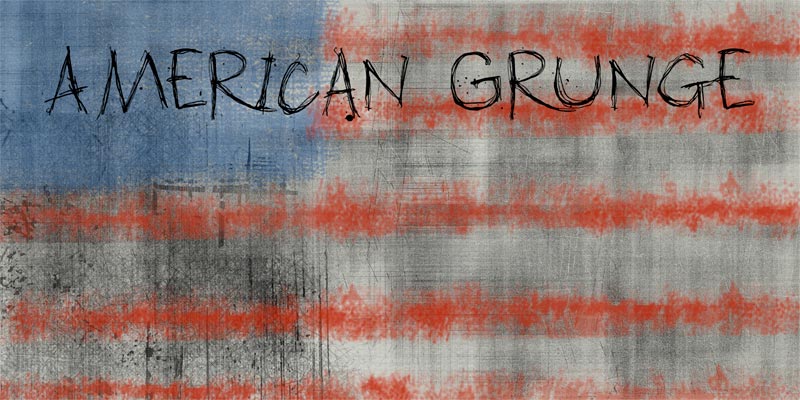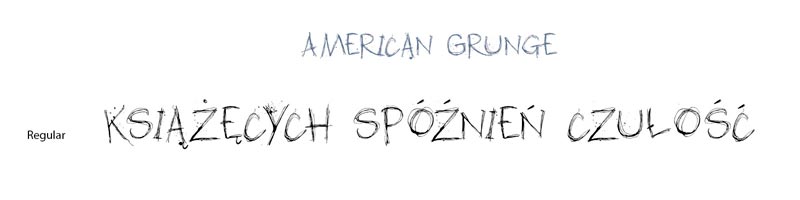
Font American Grunge
Zakupiliśmy font American Grunge, inspirowany falą muzyki grunge, która narodziła się w Seattle w latach dziewięćdziesiątych ubiegłego wieku.